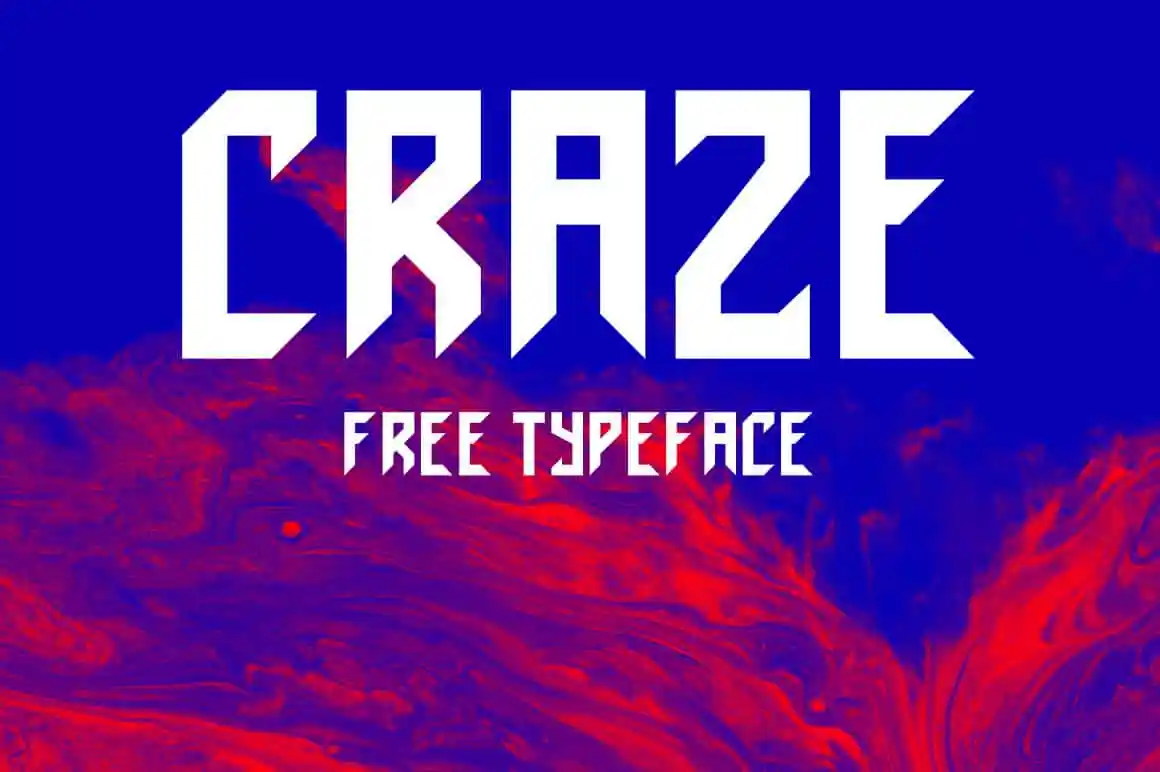
A fonte ‘Craze Typeface’, criada por Andres Lugo, é uma tipografia de display que traz beleza moderna para qualquer projeto. Essa fonte, com seus desenhos geométricos aparentemente aleatórios e extremamente definidos, oferece um toque atraente em ambientes como jogos, estilos de título para filmes ou até mesmo identidades de logotipo. A personalização criativa e intuitiva da fonte faz dela uma opção ideal para designers que desejam dar uma nova dinâmica a seus projetos visuais. Com sua natureza geométrica e seu estilo moderno, ‘Craze Typeface’ oferece um visual atraente e único para qualquer tipo de aplicação gráfica.